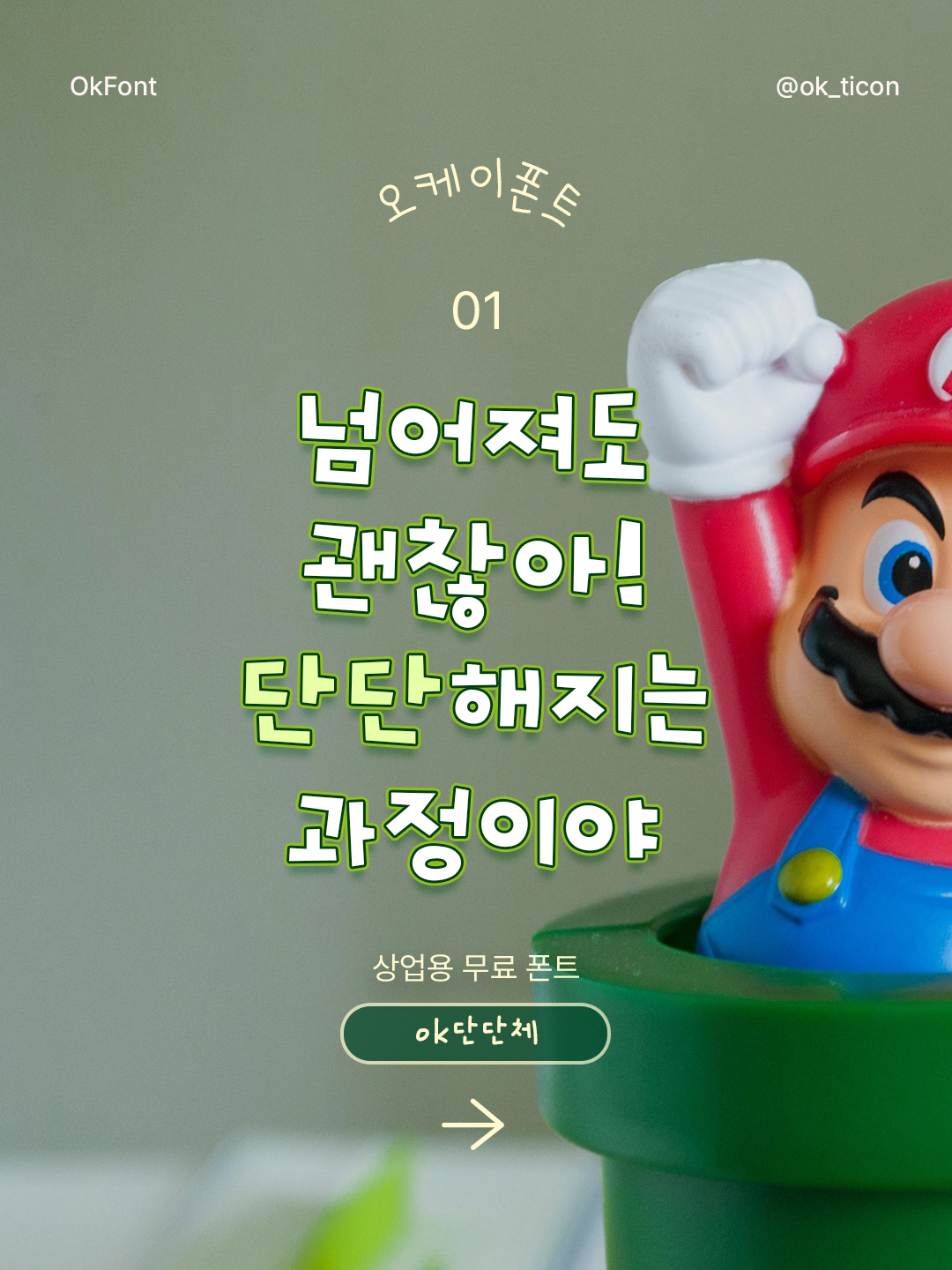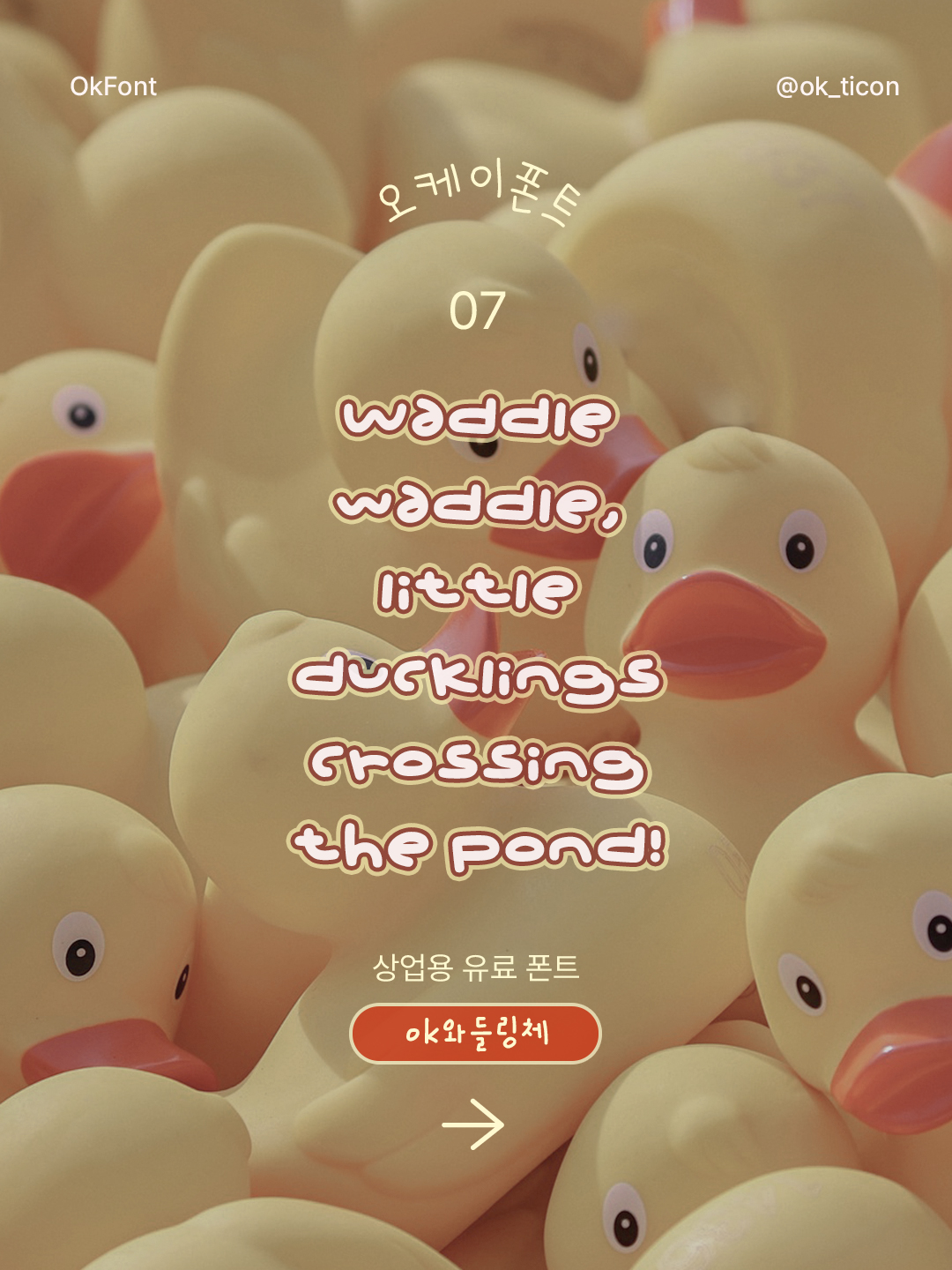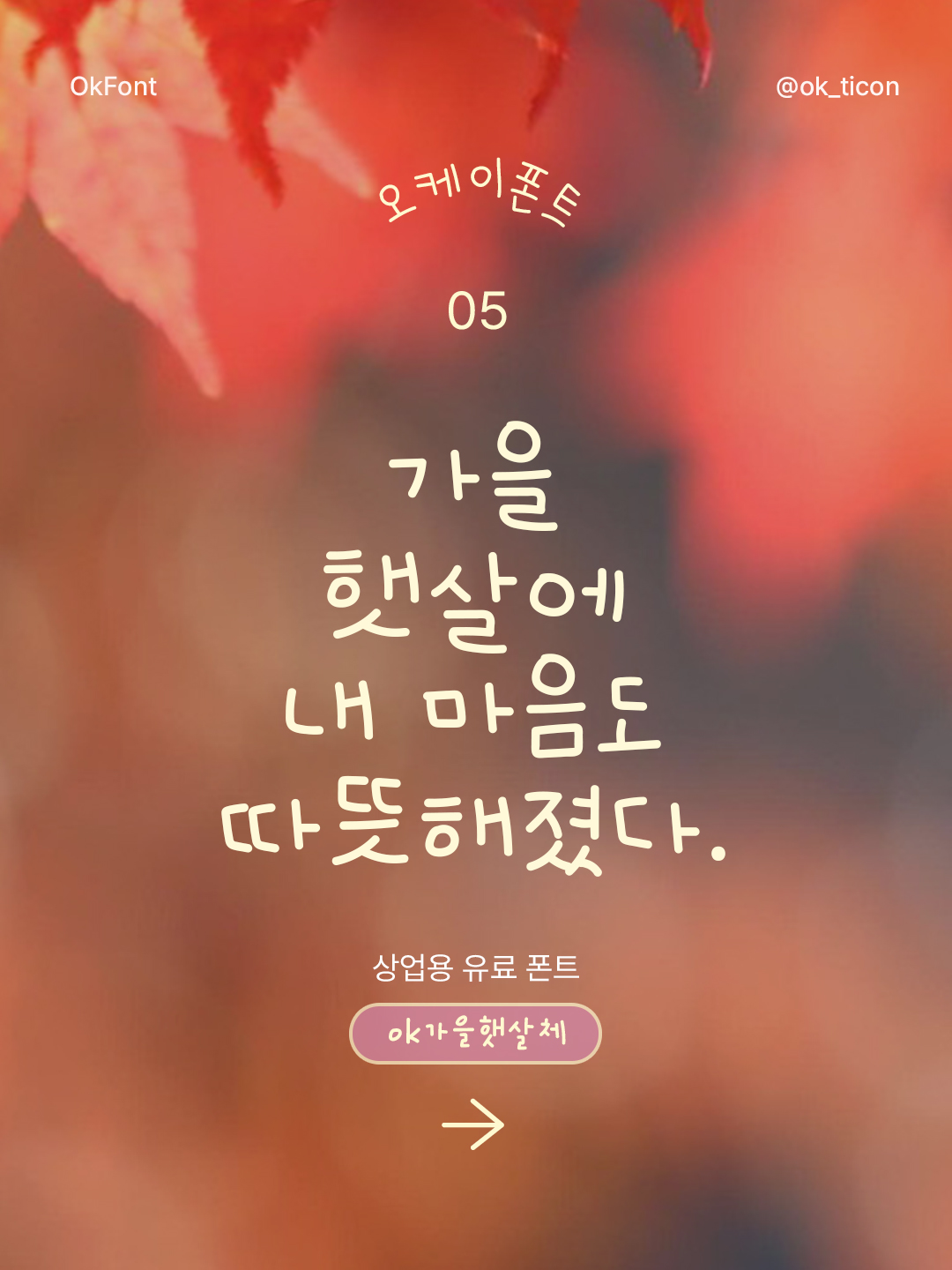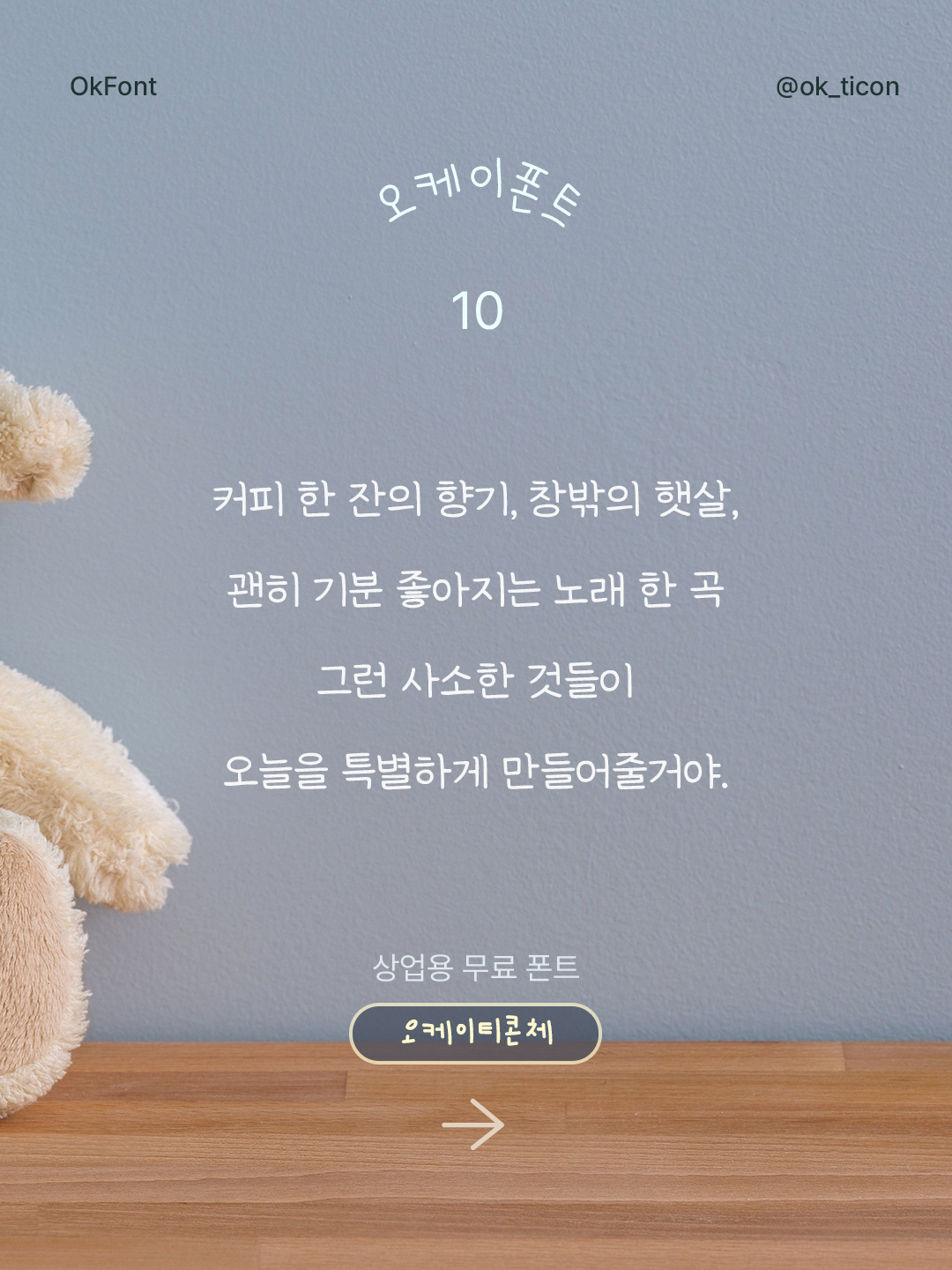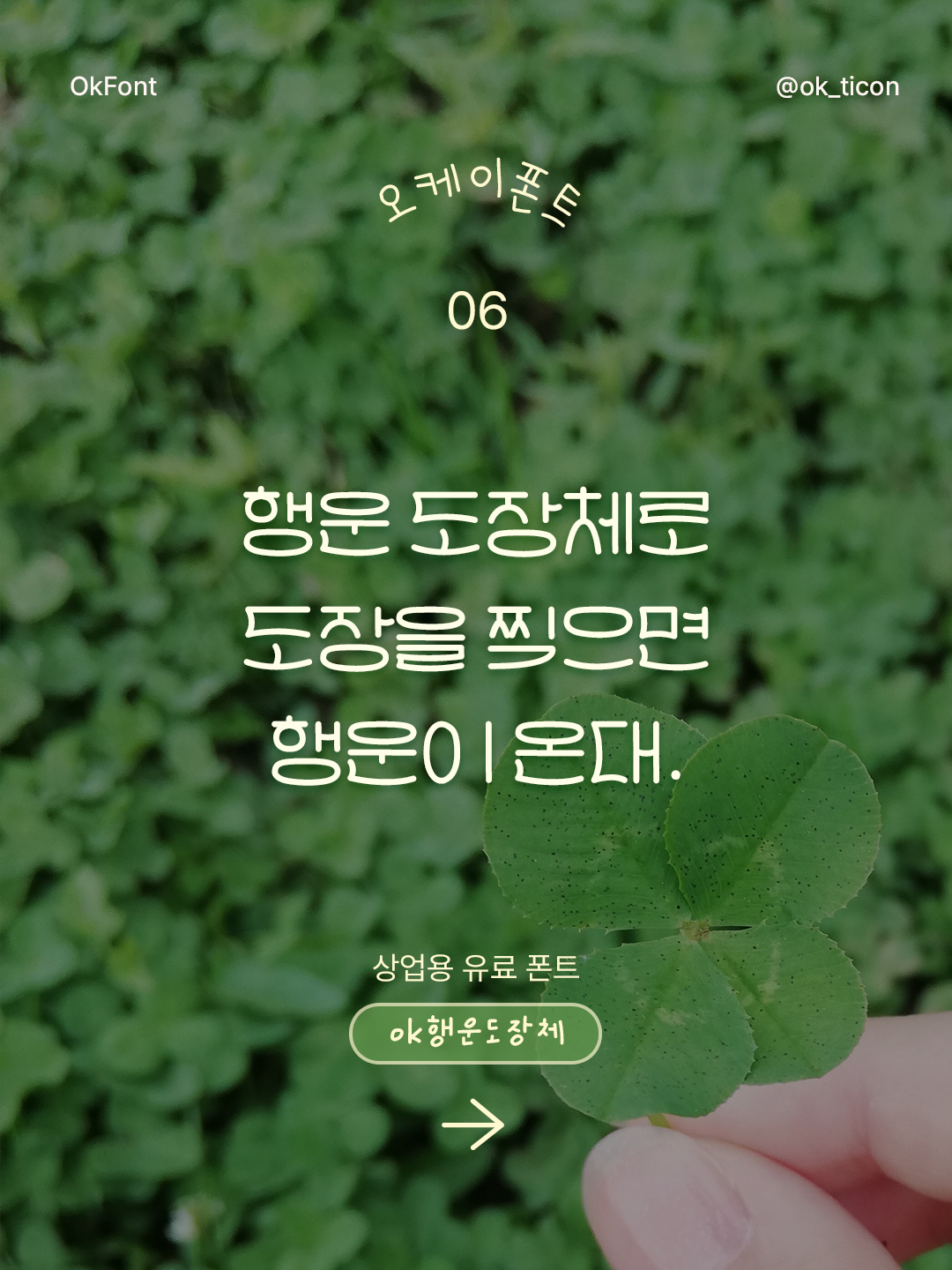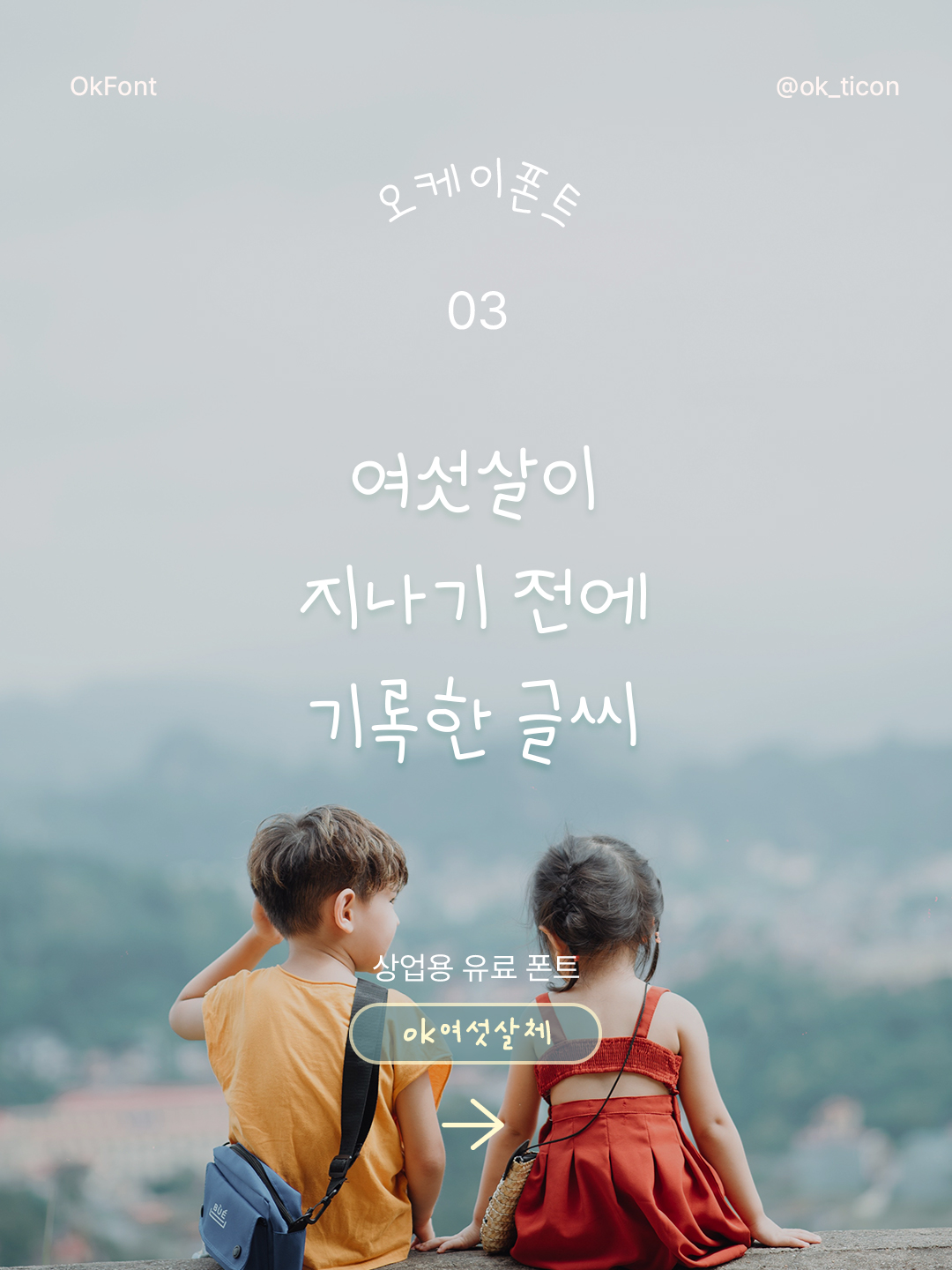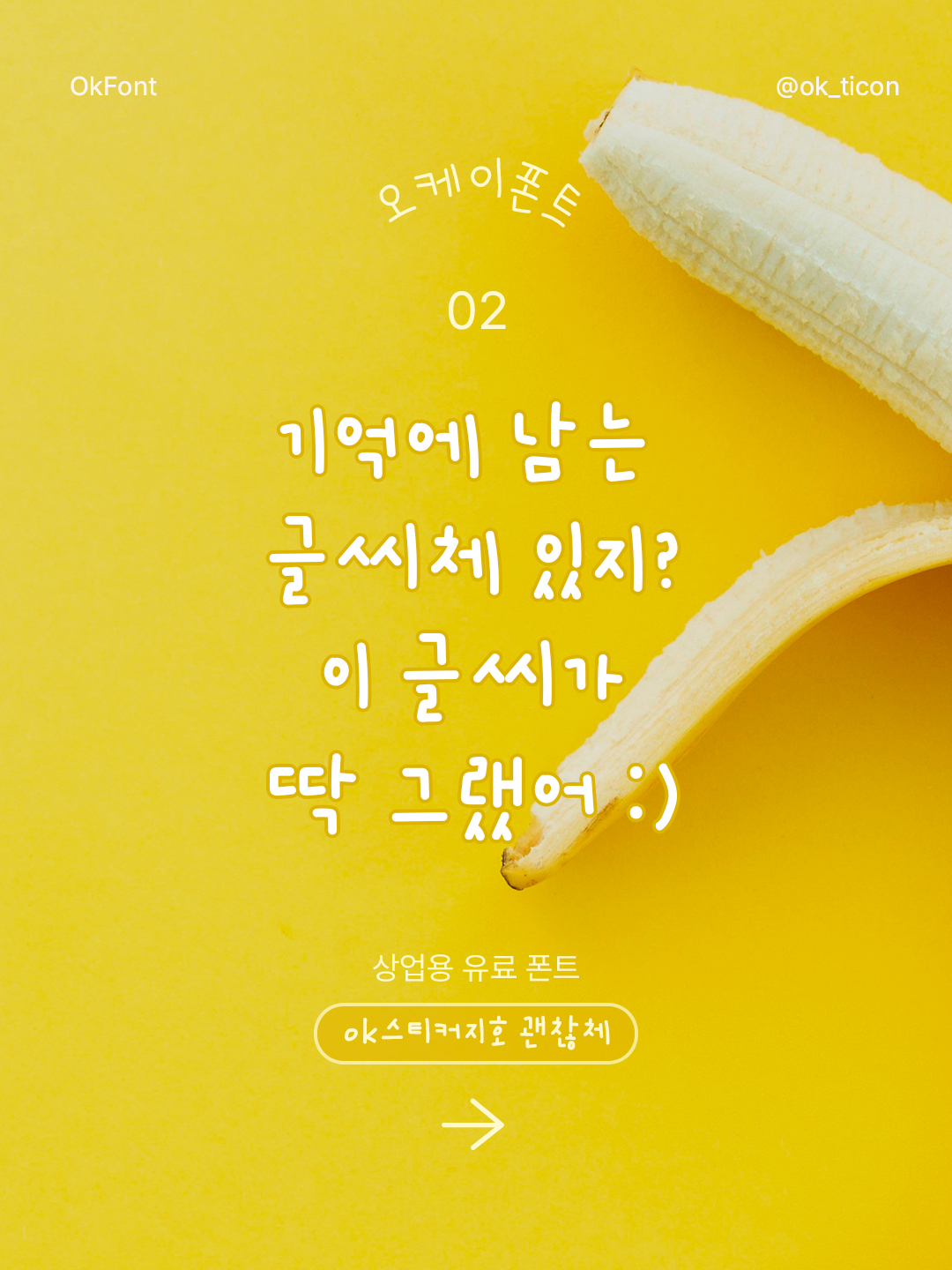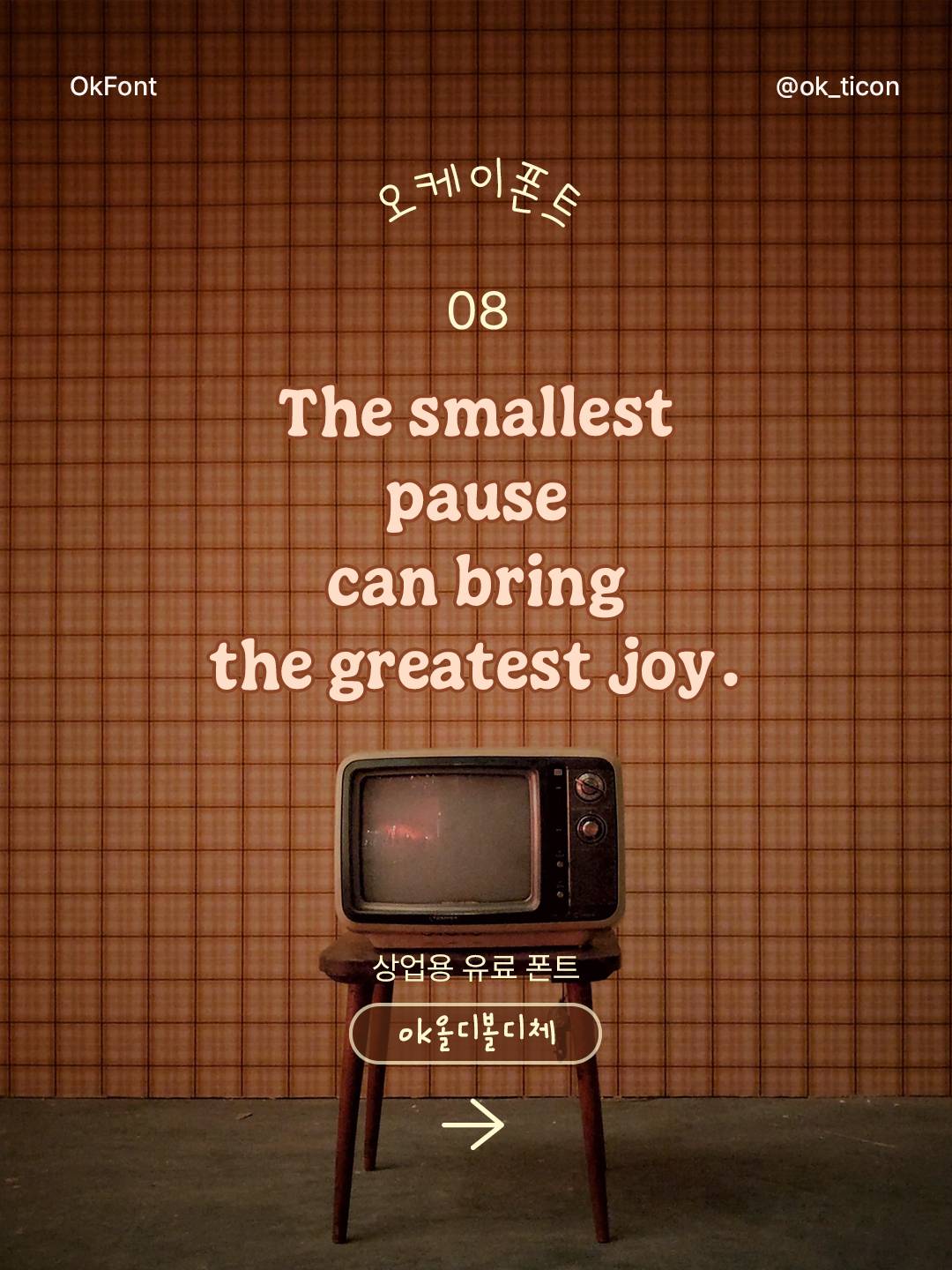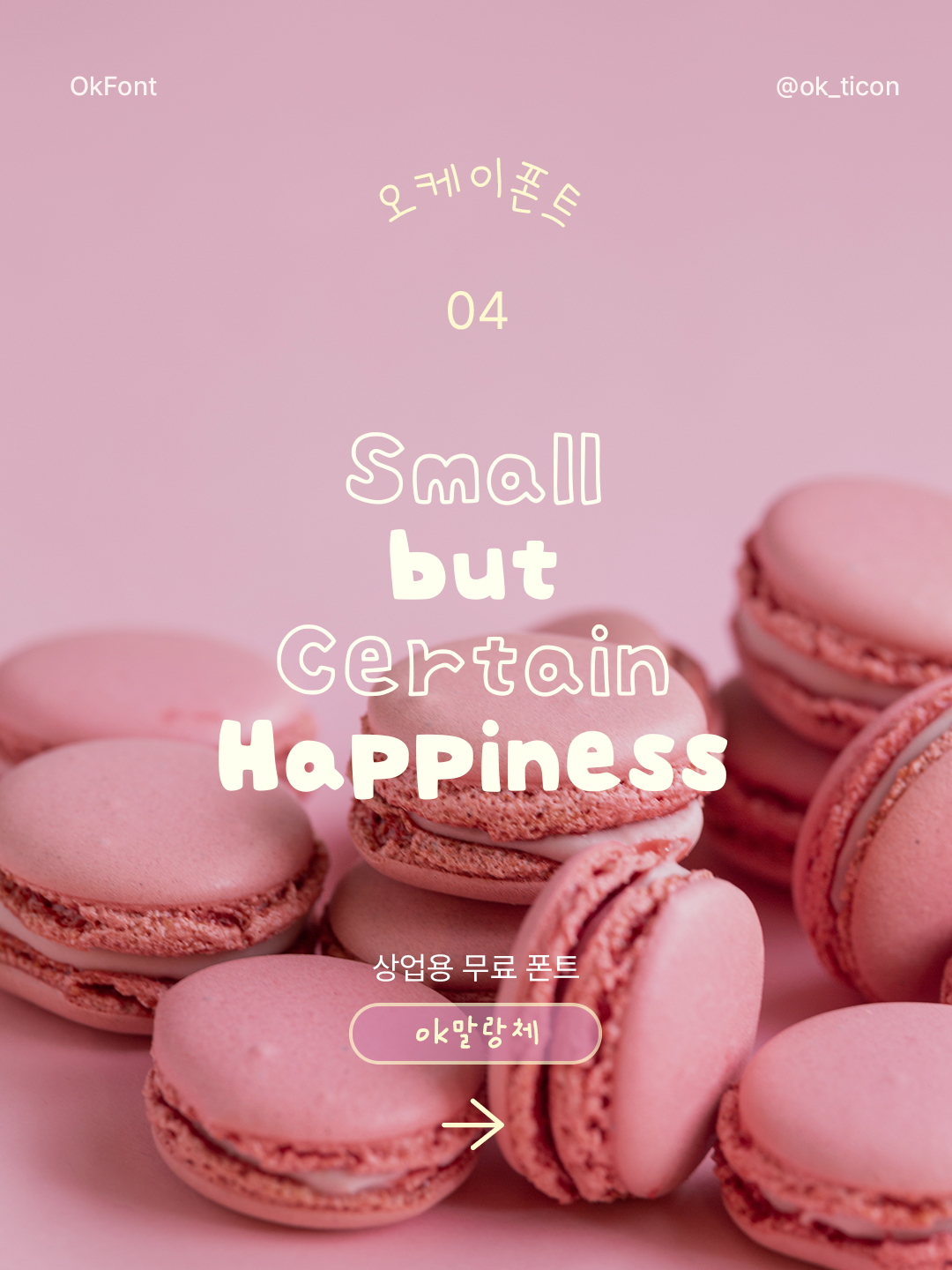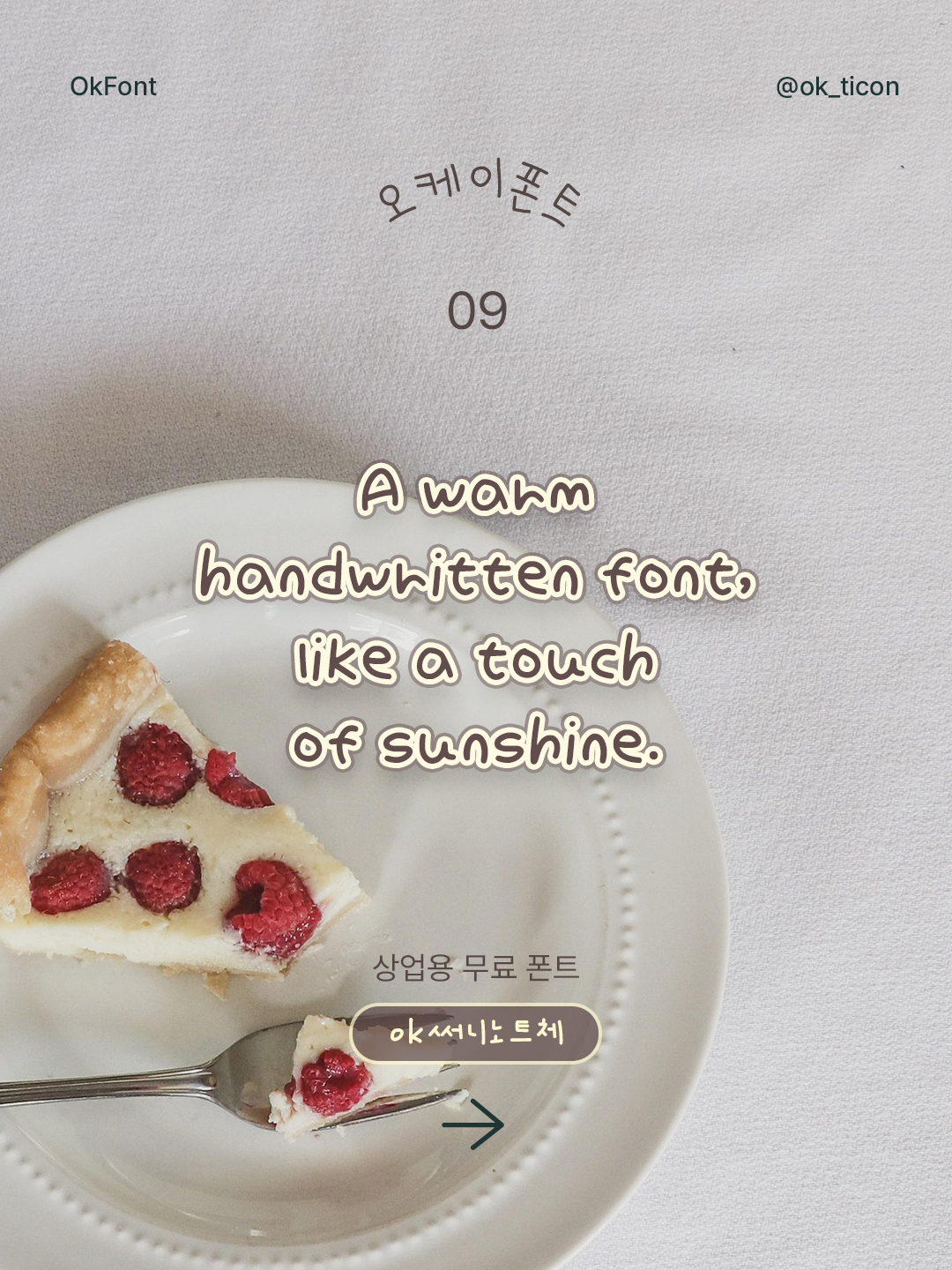
상업용으로 사용 가능한 귀여운 폰트 모음 10
상업용으로 사용 가능한
귀여운 폰트 모음 10
01. Ok단단체
(Ok DanDan)
삐뚤빼뚤 귀여운 느낌이 살아있는 폰트 입니다.
가독성이 좋아서 상세페이지, 자막 등 문구 강조용으로 활용하기 좋아요.
02. Ok스티커지호 괜찮체
(Ok StickerjihoGwaenchan)
스티커 디자인에 최적화된 폰트로
귀엽고 활용도가 높은 것이 장점입니다.
03. Ok여섯살체
(Ok Yeoseotsal)
실제 6살 아이가 직접 쓴 손글씨로
귀여운 분위기의 키즈 콘텐츠에 특히 잘 어울려요.
04. Ok말랑체
(Ok Mallang)
동글동글하고 부드러운 느낌이 매력적인 폰트입니다.
귀여운 디자인이나 감성 브랜드에 추천해요.
05. Ok가을햇살체
(Ok GaeulHaessal)
자연스럽고 편안한 손글씨 느낌으로
따뜻한 분위기를 연출할 수 있는 폰트입니다.
06. Ok행운도장체
(Ok HaengunDojang)
도장 글씨체 느낌이 나는 개성 있는 폰트로
스탬프(도장), 로고, 포인트 문구에 활용하기 좋습니다.
07. Ok와들링체
(Ok waddling)
귀엽고 통통 튀는 느낌이 살아있는 폰트로
밝고 경쾌한 디자인에 잘 어울립니다.
08. Ok올디볼디체
(Ok OldieBoldie)
세리프 스타일의 감성 가득한 폰트로
Old 하면서도 Bold 한 느낌의 레트로 감성 디자인에 어울립니다.
09. Ok써니노트체
(Ok sunnynote)
자연스러운 필기감이 느껴지는 폰트로
노트 느낌, 일상 감성 콘텐츠에 잘 어울려요.
10. 오케이티콘체
(OKTICON)
오케이티콘만의 귀여운 감성이 담긴 반듯한 손글씨체로
다양한 디자인에 무난하게 활용 하능한 것이 장점입니다.